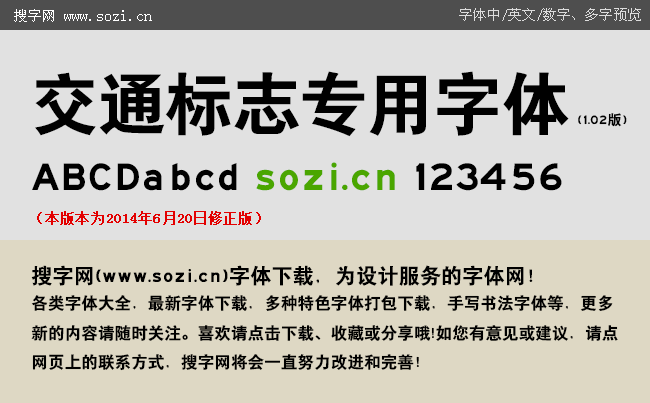
交通標(biāo)志專用字體
搜字網(wǎng)提供一款交通標(biāo)志專用字體中文字體下載,交通標(biāo)志專用字體是一款應(yīng)用于交通標(biāo)志的專用黑體,結(jié)構(gòu)端正、重心平穩(wěn)、美觀實用,適用于包裝印刷、廣告設(shè)計、平面設(shè)計、書籍報紙等領(lǐng)域。